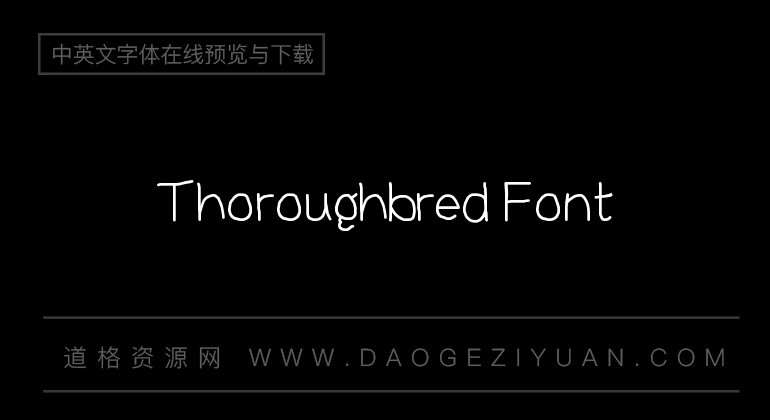
Thoroughbred 字体是一种精美的手写英文字体,它的字形优美、流畅,具有浓郁的美式风格。这款字体旨在为设计师、广告人员、品牌经理和其他创意专业人士提供一种时尚、高质量的字体选择。 Thoroughbred 字体的字母形状优美,线条流畅,整体呈现出一种优雅、稳重的感觉。它提供了多种字重和风格的变体,适用于各种设计场景,包括标志、海报、印刷品和网页设计等。该字体还支持多种语言,包括英语、西班牙语、法语和德语等。 Thoroughbred 字体是一款商业字体,需要购买授权后才能使用,授权费用根据使用范围和期限而定。但是,该字体的高质量和多样性使其成为值得投资的一款字体。内容介绍
Thoroughbred Font是一款非常不错的手写艺术字体,具有很好的视觉感,适合于文化类的宣传设计、商业类品牌的广告和产品包装设计以及个性化文字排版等较多场景。